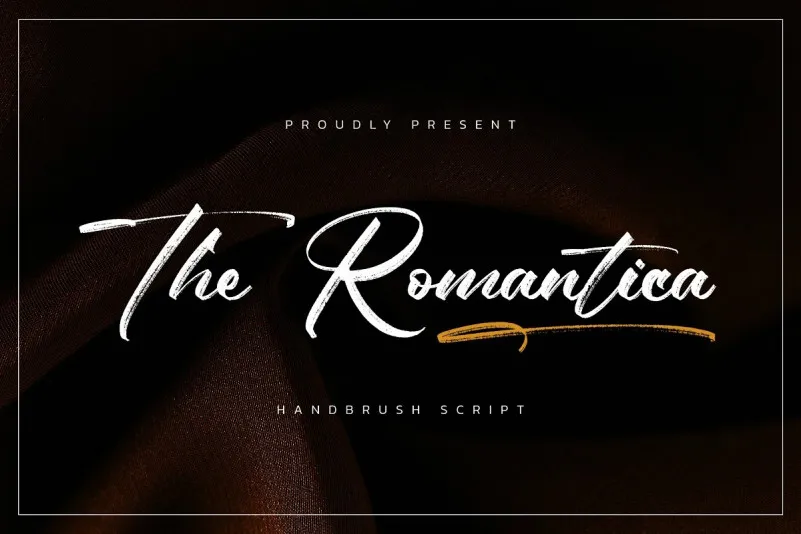
The Romantica Font
A fonte The Romantica é uma elegante tipografia escrita a mão, produzida pela Almarkha Type. Seus caracteres são formados com pinceladas nas folhas de papel e posteriormente digitadas cuidadosamente no formato vetorial. Esta característica garante que The Romantica apresente um charme, autenticidade e uma personalidade relaxada. A fonte inclui duas estilos principais: regular, esbugalhado e com swash. Isso lhe dá um visual mais natural a seu texto, proporcionando um toque único e sofisticado sem perder o estilo elegante de uma tipografia escrita a mão. Seja para adicionar um toque romântico ou um pouco de personalidade à sua próxima publicação, The Romantica é perfeita para designers em busca de algo verdadeiramente especial e encantador.